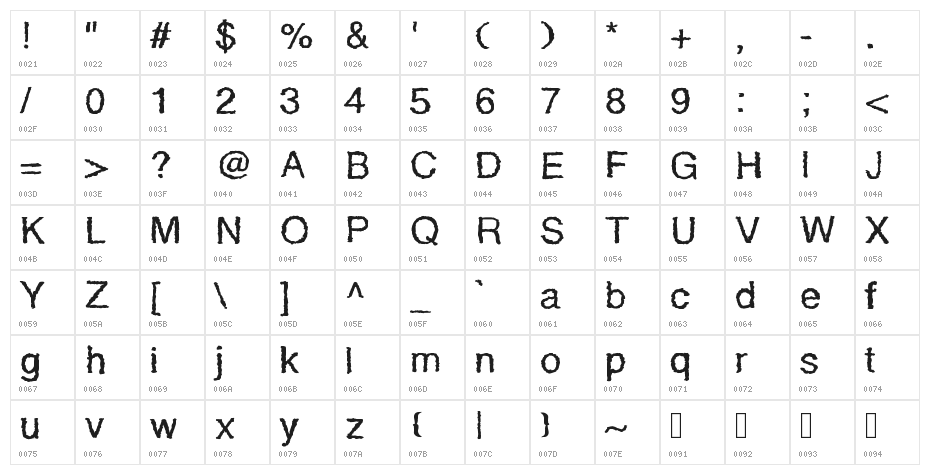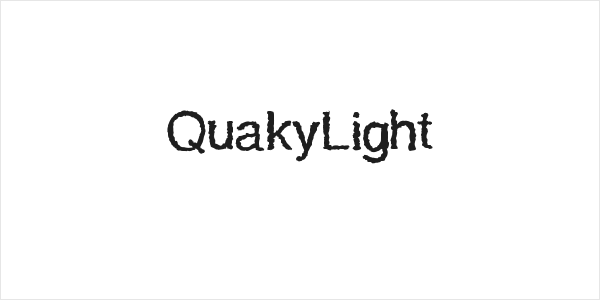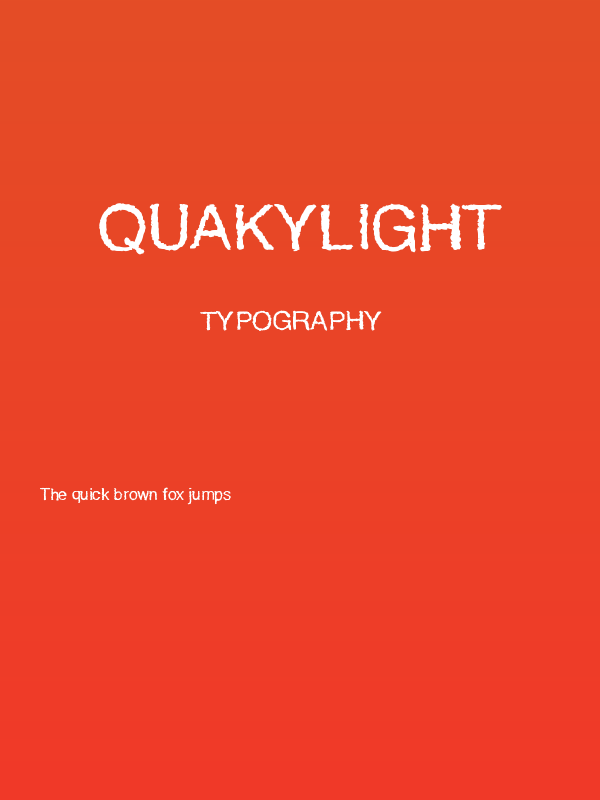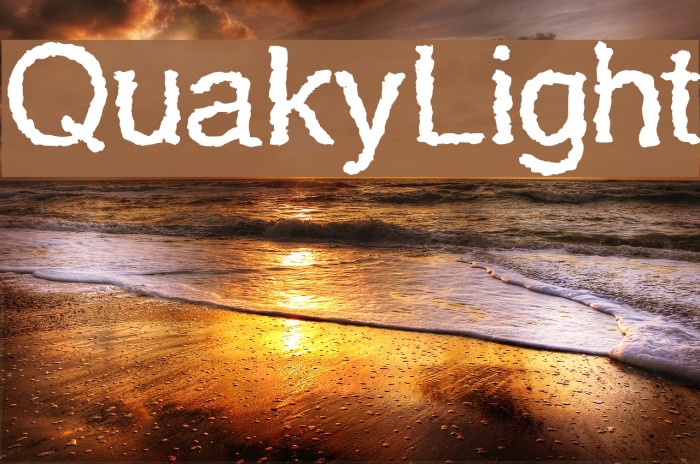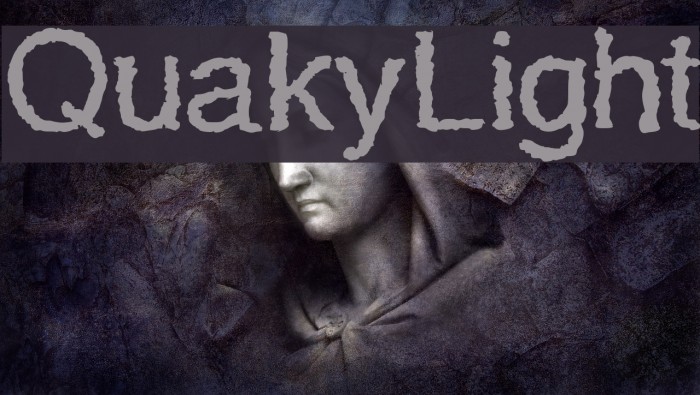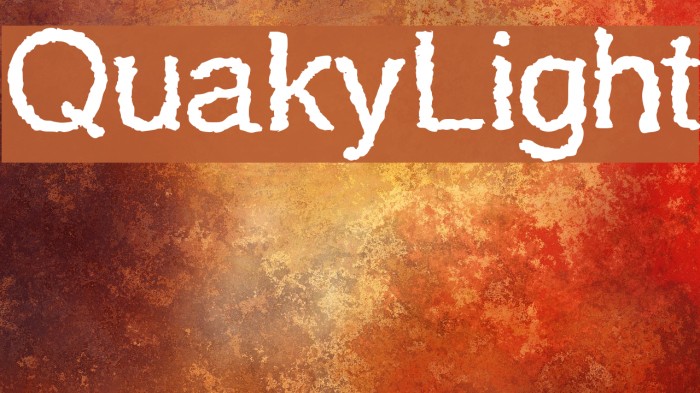
QuakyLight Font
| Anwendungsfall | Logos, Headlines, Posters |
| Vorgeschlagene Projekte | Ideal for artistic projects, posters, children's books, and creative branding. |
| Autor | Fonts by FreshTypeINK |